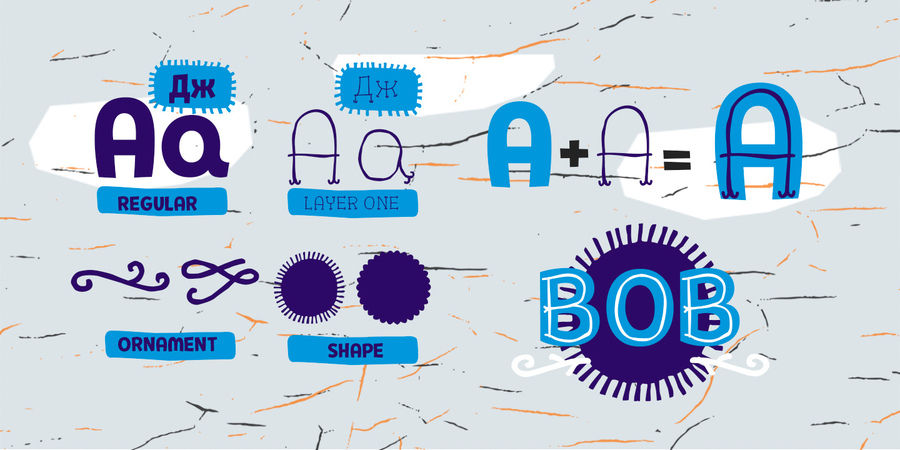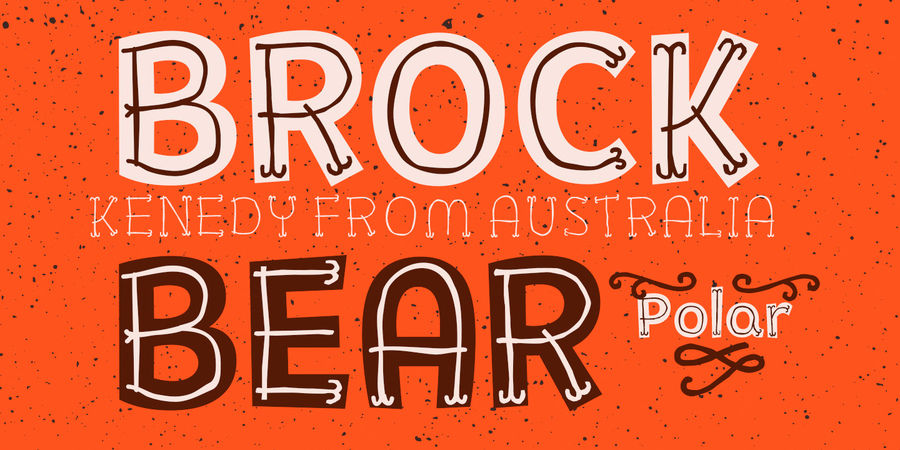
Опис гарнітури Pequena Pro – це грайливе, миле й наївне шрифтоое сімейство з двома алфівітнимі шарами (масний гротеск і тонкий мальований) та двома неалфавітних (орнаменти й фони). Ідеально підходить для дитячих книжок та святкових товарів. Pequena Pro підтримує безліч європейських мов, а також кирилицю. Шрифт розробив Родріго Арая Салас за участю Андрія Кудрявцева у 2016 році.
стінгазета, журнал, комікс, пакування, листівка, анімація, мультфільм, вивіска, обкладинка, плакат, реклама, етикетка, афіша, меню, відео, стікер, наліпка, шкільна дошка, привітання, альбом, щоденник Адаптованість гарнітури до носіїв:
Асоціації з сімейством шрифтів Pequena ProОсобистість і характер гарнітури:
виразний, потішний, іронічний, здоровий, бадьорий, характерний, гулящий, дозвільний, пещений, круглий, щедрий, гладенький, цікавий, пластичний, студентськиий, тусовочний, прикольний, динамічний, живий, непосидючий, доброзичливий, привітний, довірчий, неформальний, молодіжний, яскравий, п'яний, веселий, задерикуватий, смішний, добродушний, добрий, радісний, грайливий, пустотливий, рухливий, оригінальний, свіжий, стиглий, смачний, помітний, дитячий, наївний, карикатурний, милий, мультяшний, новорічний, дотепний, домашній, літній, щасливий, святковий, М'який, творчий, природний, натуральний, крафтовий, худий, ручний, кустарний, саморобний, ремісничий, неотесаний, нерівний, рукотворний, неохайний, кріповий, дивний, стрибучий, тонкий, легкий, дротяний, чистий, весняний, органічний, химерний, артізанальний, екзотичний, недбалий, вернакулярний, макабричний, емоційний, спекотний, дівчачий, кольоровий, південний, танцюючий, активний, інфантильний, артистичний, зелений, гнучкий, тропічний, примітивний, кучерявий, затишний, квітковий, сільський, сімейний, апетитний, казковий, рослинний, симпатичний
дача, хенд мейд, природа, фаст фуд, крамниця, графіті, гурток, олівці, іграшка, пригоди, розваги, вечірка, торгівля, реклама, магазин, зоопарк, гра, кафе, дитяча книжка, канцтовари, школа, табір, гумор, анімація, сніданок, їжа, закуска, клоун, розфарбування, зоомагазин, тварини, відпочинок, щоденник, цирк, мультфільм, Новий рік, дитсадок, дитячий ранок, Christmas, селфі, канікули, підгузок, графіка, ілюстрація, дім, ранок, дієта, трава, весна, квіти, геловін, хоррор, фільм жахів, жуки, павуки, комахи, атракціон, закляття, Самайн, море, учень, школяр, школярка, свято, тусовка, фарби, фестиваль, ярмарок, десерт, солодощі, базар, Хюґе, прикраса, одяг, сукня, кухня, Чарівна казка, сад, городина Гарнітура асоціюється з віком: